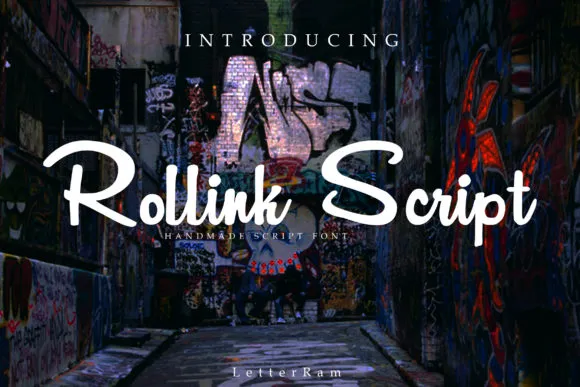
Rollink Script Font – Fonte Grátis
Rollink Script Font
A Rollink Script Font é uma elegante escolha para quem procura uma fonte que transmite charme com modéstia. Ela foi criada pela LetterRam e apresenta um estilo de escrita moderno e sofisticado, dando um toque único aos projetos gráficos. Seja para criar logotipos memoráveis, estilos de marca inovadores, gráficos em movimento, designs visuais criativos ou até mesmo embalagens de produtos originais, a Rollink atende perfeitamente aos requisitos. Sua facilidade de uso e sua capacidade única de agregar um toque autêntico e delicado à qualquer projeto tornam-na uma fonte indispensável para designers profissionais em todas as áreas do design gráfico.